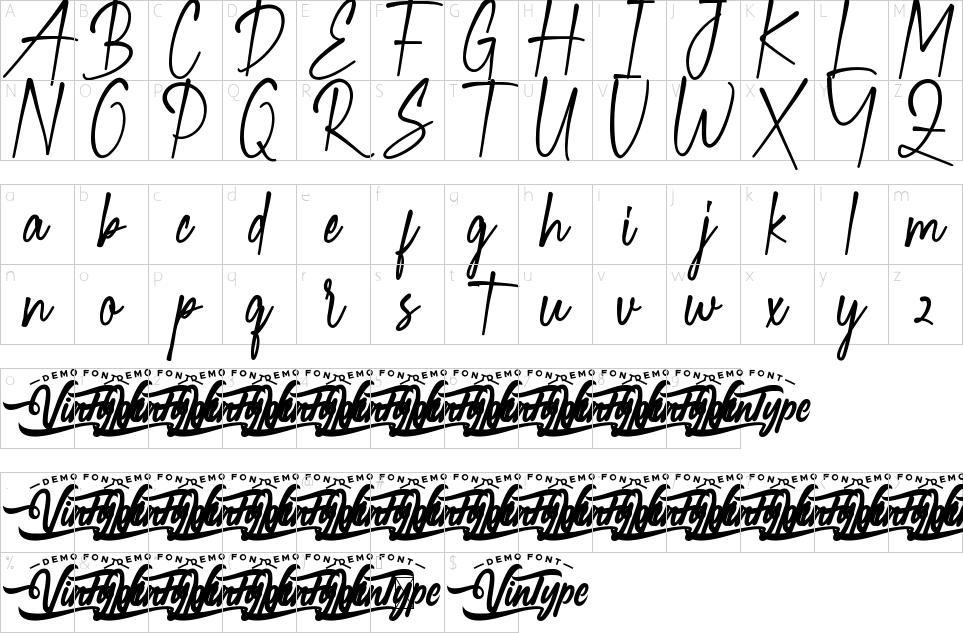
A descoberta da Green Latte é uma agradável surpresa para criadores de designs digitais que buscam personalidade em seu trabalho sem comprometer o profissionalismo. Desenhada por vintype, esta fonte está disponível gratuitamente tanto para sistemas Windows quanto para Mac. Com um toque de coloração verde e uma letra alegre, a Green Latte é perfeita para aplicar uma pitada de vida ao seu design digital sem deixá-lo excessivamente carregado. Com 2,430 downloads, já percebemos que os designers apreciam esta fonte pela sua simplicidade e elegância, tornando-a um excelente recurso a ser explorado pelos amantes do design gráfico em busca de uma nova maneira de dar vida ao seu trabalho.